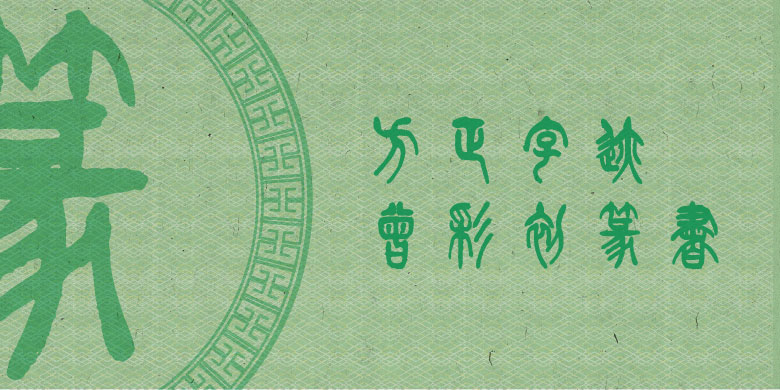
方正字迹-曾彩初篆书
方正字迹-曾彩初篆书,由著名书画家、教育家曾彩初先生创作。曾彩初先生为中国书法家协会会员、湖南省书法家协会会员。这款字体取法《说文解字》,融合大篆与小篆而自成一体,以圆笔藏锋为主书写而成,字形修长、上密下疏呈现出甲骨文、金文的古朴厚重、浑厚宏伟之气,又具小篆端庄典雅的美感,既植根传统又彰显个性。适用于有传统文化底蕴的艺术观赏和宣传、刻石、刻印、广告包装、书籍装帧设计、书画标题。